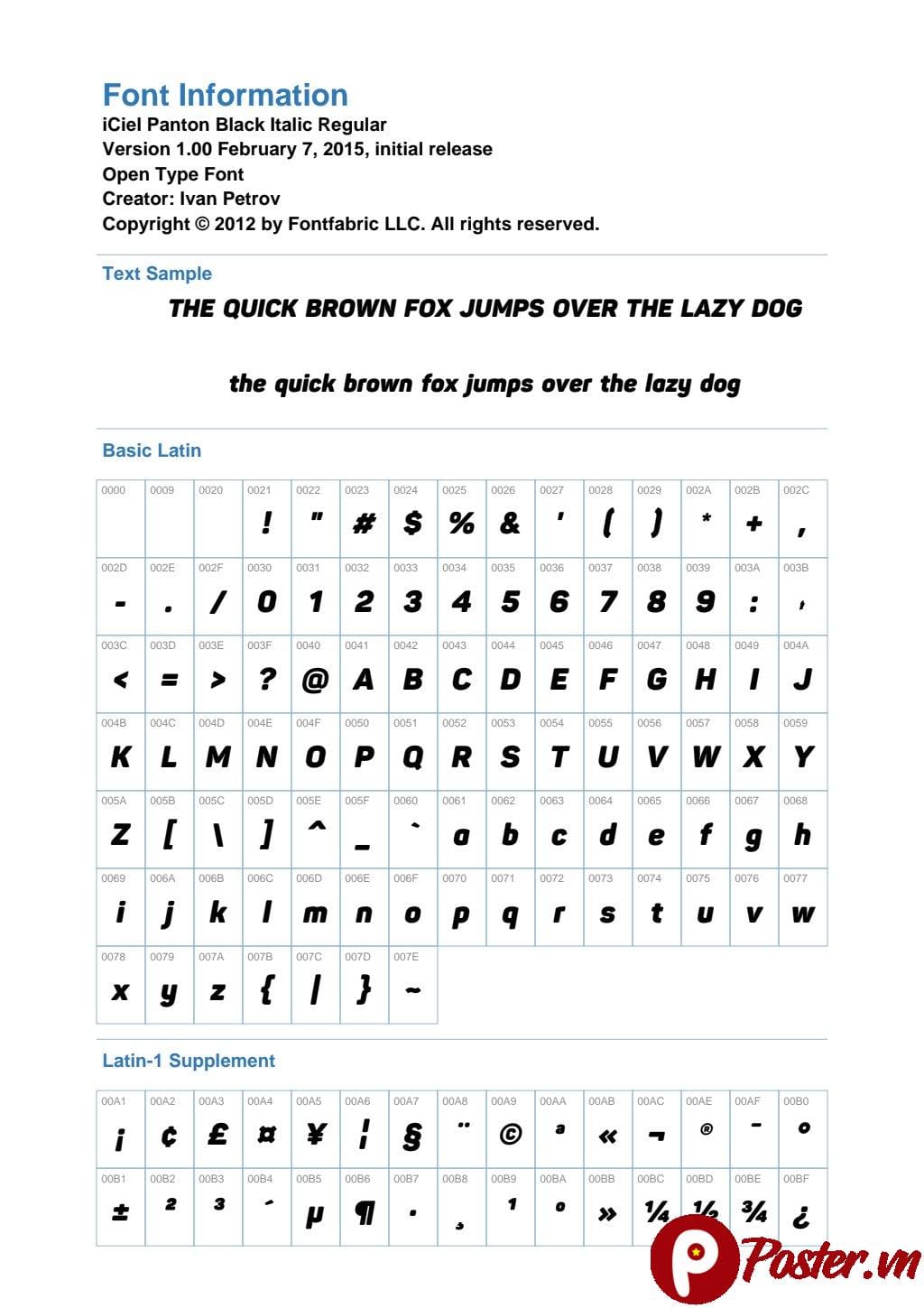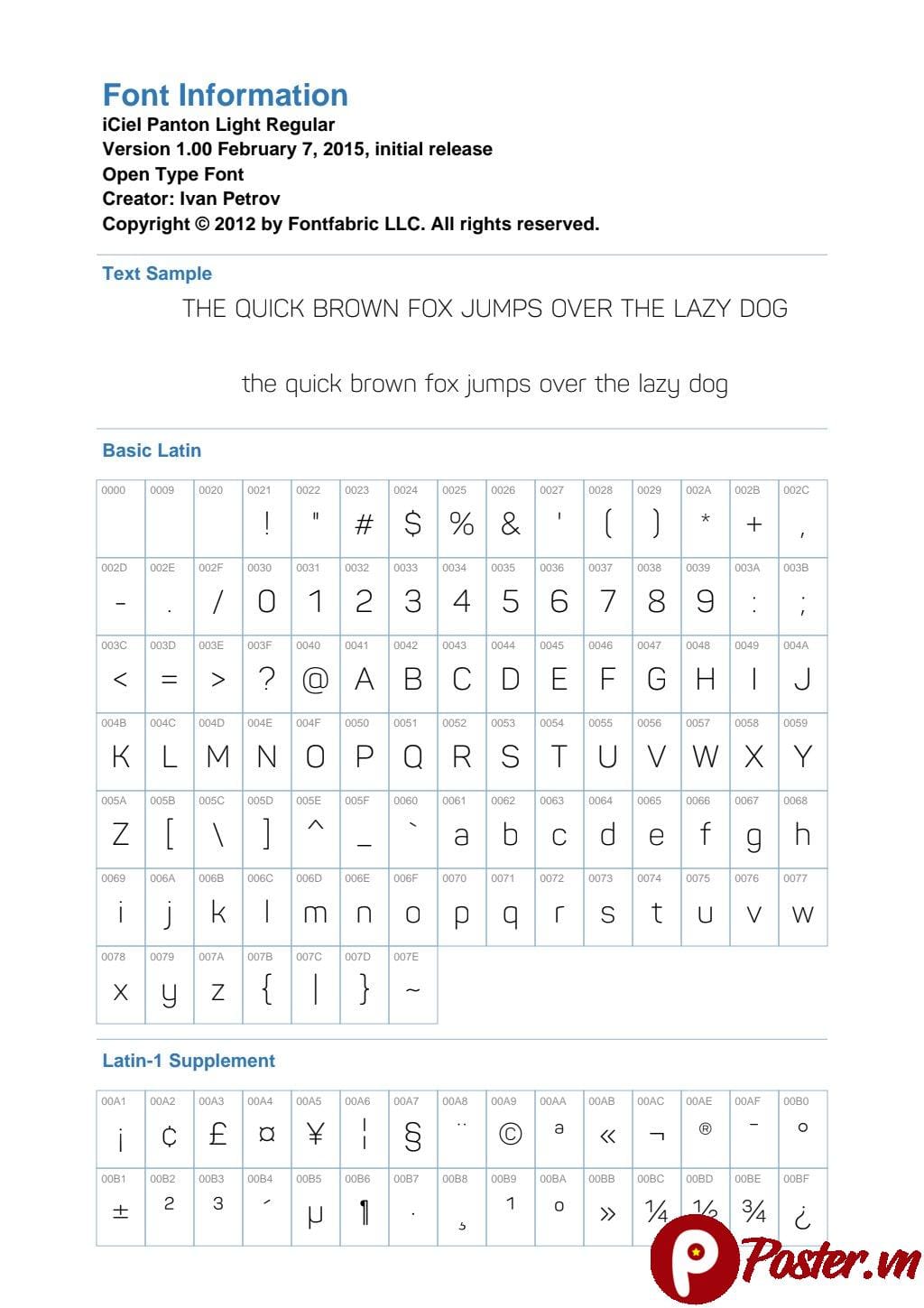
Giới Thiệu Bộ SVN Font Việt Hóa Tuyển Chọn: Nâng Tầm Thiết Kế Của Bạn
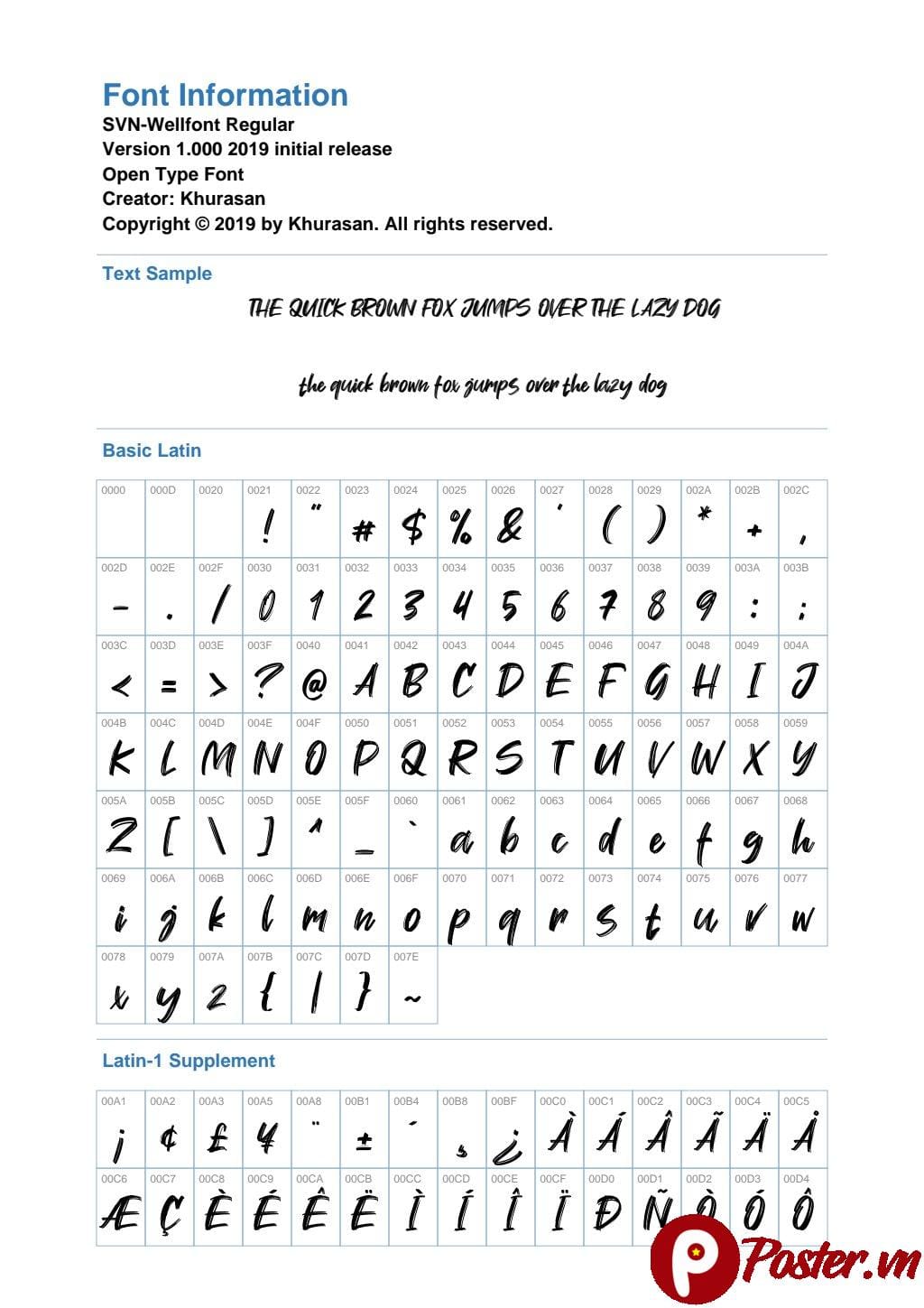
Trong thế giới thiết kế đồ họa đầy cạnh tranh ngày nay, font chữ không chỉ là công cụ truyền tải thông điệp mà còn là linh hồn của tác phẩm, góp phần định hình phong cách và cảm xúc. Đặc biệt, với các dự án hướng tới thị trường Việt Nam, việc sử dụng các font chữ được Việt hóa hoàn chỉnh là yếu tố then chốt để đảm bảo tính chuyên nghiệp và truyền tải thông điệp một cách rõ ràng, mạch lạc. Hiểu được nhu cầu đó, Poster.vn hân hạnh giới thiệu bộ sưu tập độc quyền: 400+ SVN Font Việt Hóa – một kho tàng font chữ đa dạng, chất lượng cao, sẵn sàng phục vụ mọi ý tưởng sáng tạo của bạn.
Bộ SVN Font Việt Hóa này là tập hợp các font chữ được cộng đồng thiết kế Việt Nam yêu thích và tin dùng, đã được điều chỉnh kỹ lưỡng để hỗ trợ đầy đủ các ký tự tiếng Việt có dấu. Từ những kiểu chữ sans-serif hiện đại, thanh lịch đến serif cổ điển, sang trọng, hay các font script bay bổng, nghệ thuật, bộ sưu tập này chắc chắn sẽ đáp ứng mọi yêu cầu khắt khe nhất. Dù bạn là nhà thiết kế chuyên nghiệp, sinh viên đồ họa hay chỉ đơn giản là người đam mê sáng tạo, kho tàng font chữ này sẽ là trợ thủ đắc lực, giúp bạn biến hóa ý tưởng thành hiện thực một cách dễ dàng và ấn tượng.
Các Tính Năng Nổi Bật Của Bộ 400+ SVN Font Việt Hóa
Bộ SVN Font Việt Hóa này không chỉ là một tập hợp các font chữ mà còn là một công cụ mạnh mẽ giúp bạn khai phá tiềm năng sáng tạo không giới hạn. Dưới đây là những tính năng nổi bật, cả về mặt kỹ thuật và thẩm mỹ, mà bạn sẽ được trải nghiệm:
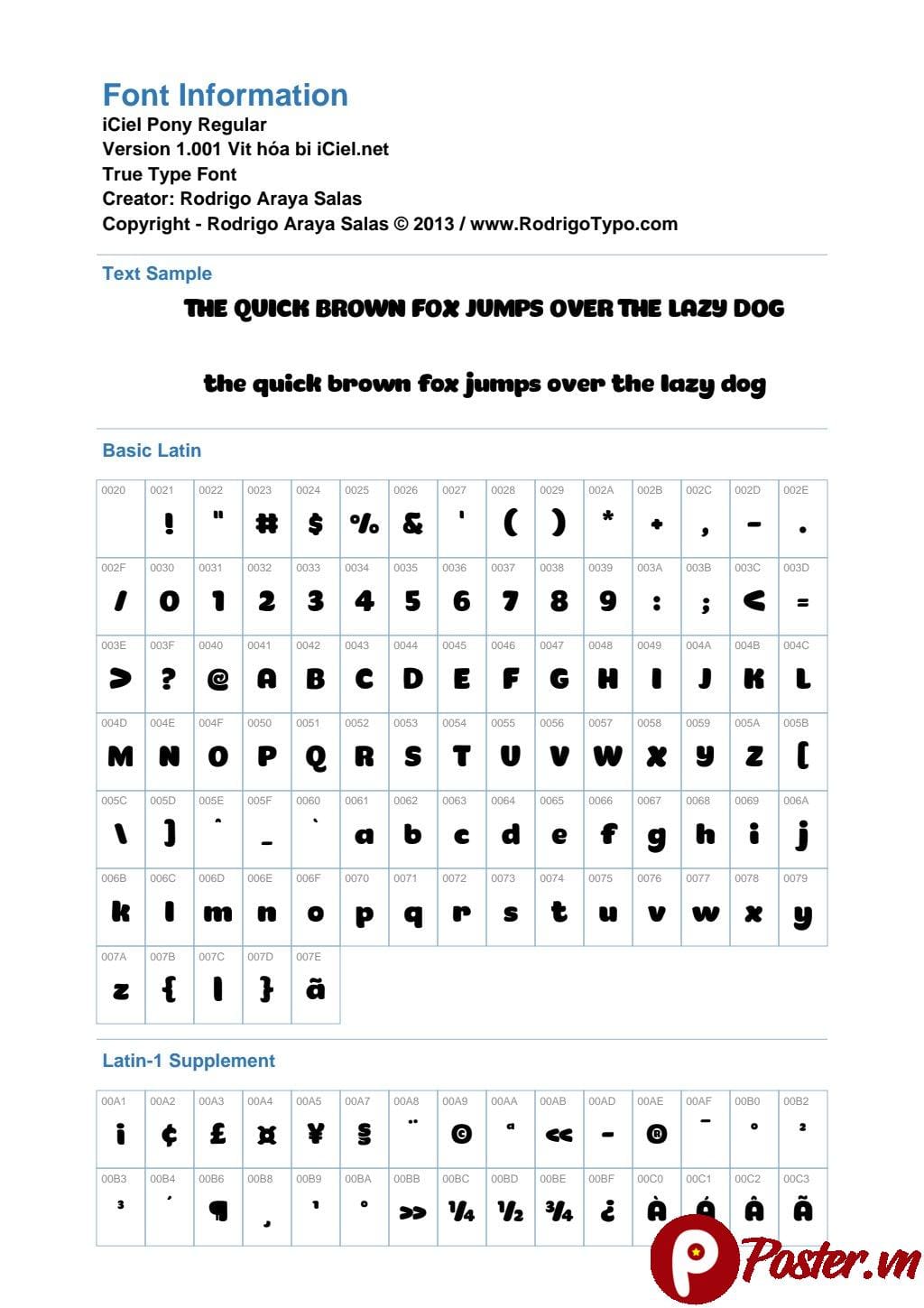
- Hơn 400 Font Đa Dạng: Bộ sưu tập đồ sộ này bao gồm một lượng lớn các font chữ, từ những kiểu kinh điển được yêu thích đến những xu hướng mới nhất. Sự đa dạng này đảm bảo bạn luôn tìm thấy font phù hợp cho mọi dự án, từ thiệp cưới lãng mạn đến poster quảng cáo năng động.
- Việt Hóa Chuẩn Xác: Đây là yếu tố quan trọng nhất. Tất cả các font trong bộ này đều đã được Việt hóa kỹ lưỡng, hỗ trợ đầy đủ bảng chữ cái tiếng Việt cùng các dấu thanh, giúp bạn gõ tiếng Việt mượt mà, không lỗi font, không cần điều chỉnh thủ công. Điều này tiết kiệm đáng kể thời gian và công sức trong quá trình thiết kế.
Tính Năng Thẩm Mỹ
- Phong Cách Đa Dạng: Khám phá vô số phong cách từ tối giản, hiện đại, clean & minimalist cho đến cổ điển, vintage, hoặc thậm chí là các font viết tay (script), brush font đầy cá tính và nghệ thuật. Bạn có thể dễ dàng chuyển đổi giữa các phong cách để tìm ra sự kết hợp hoàn hảo cho thông điệp của mình.